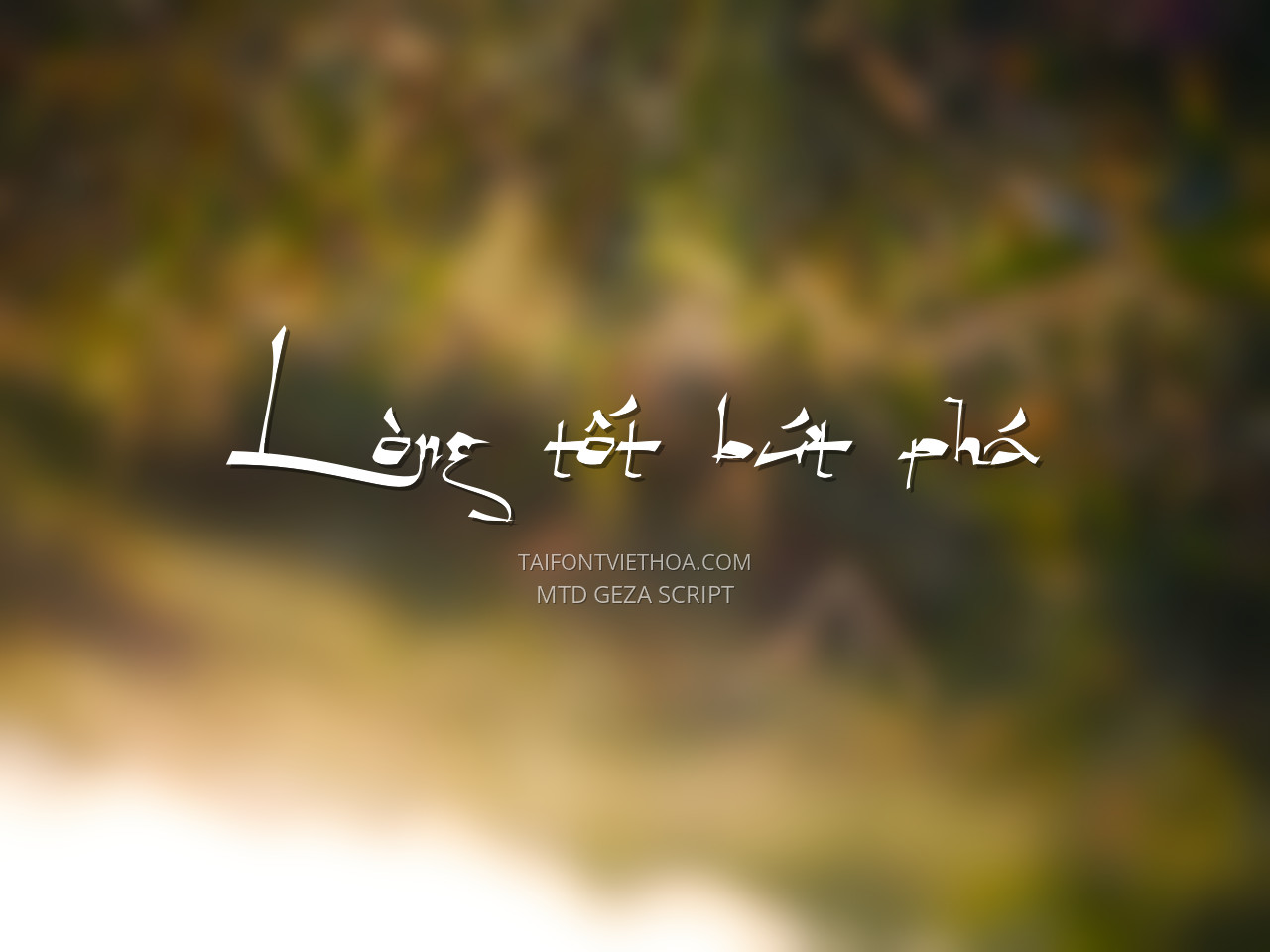
Font việt hóa MTD Geza Script
Giới thiệu về font Geza Script
Geza Script là một font chữ script mềm mại và đầy nghệ thuật, được thiết kế bởi Motokiwo Type (MTD). Với phong cách bay bổng, mang hơi hướng thư pháp hiện đại, Geza Script thể hiện sự thanh thoát, uyển chuyển trong từng nét chữ. Font này mang đến cảm giác lãng mạn và tinh tế, là lựa chọn tuyệt vời cho các thiết kế thiên về cảm xúc hoặc cần tạo điểm nhấn nghệ thuật. Phiên bản Việt hóa được chính MTD thực hiện, hỗ trợ đầy đủ tiếng Việt và hơn 70 ngôn ngữ khác, giúp font này dễ dàng tích hợp vào nhiều dự án thiết kế trong nước lẫn quốc tế.
Đặc điểm thiết kế và ứng dụng của font Geza Script
Font Geza Script sở hữu đường nét mềm mại, uốn cong duyên dáng cùng với các ligatures và ký tự thay thế phong phú. Kiểu chữ có độ nghiêng nhẹ, kết hợp giữa nét thanh và nét đậm hài hòa, tạo nên nhịp điệu thị giác dễ chịu và sang trọng. Geza Script đặc biệt nổi bật khi được sử dụng làm tiêu đề, chữ ký thương hiệu hoặc các thiết kế mang phong cách nữ tính và tinh tế.